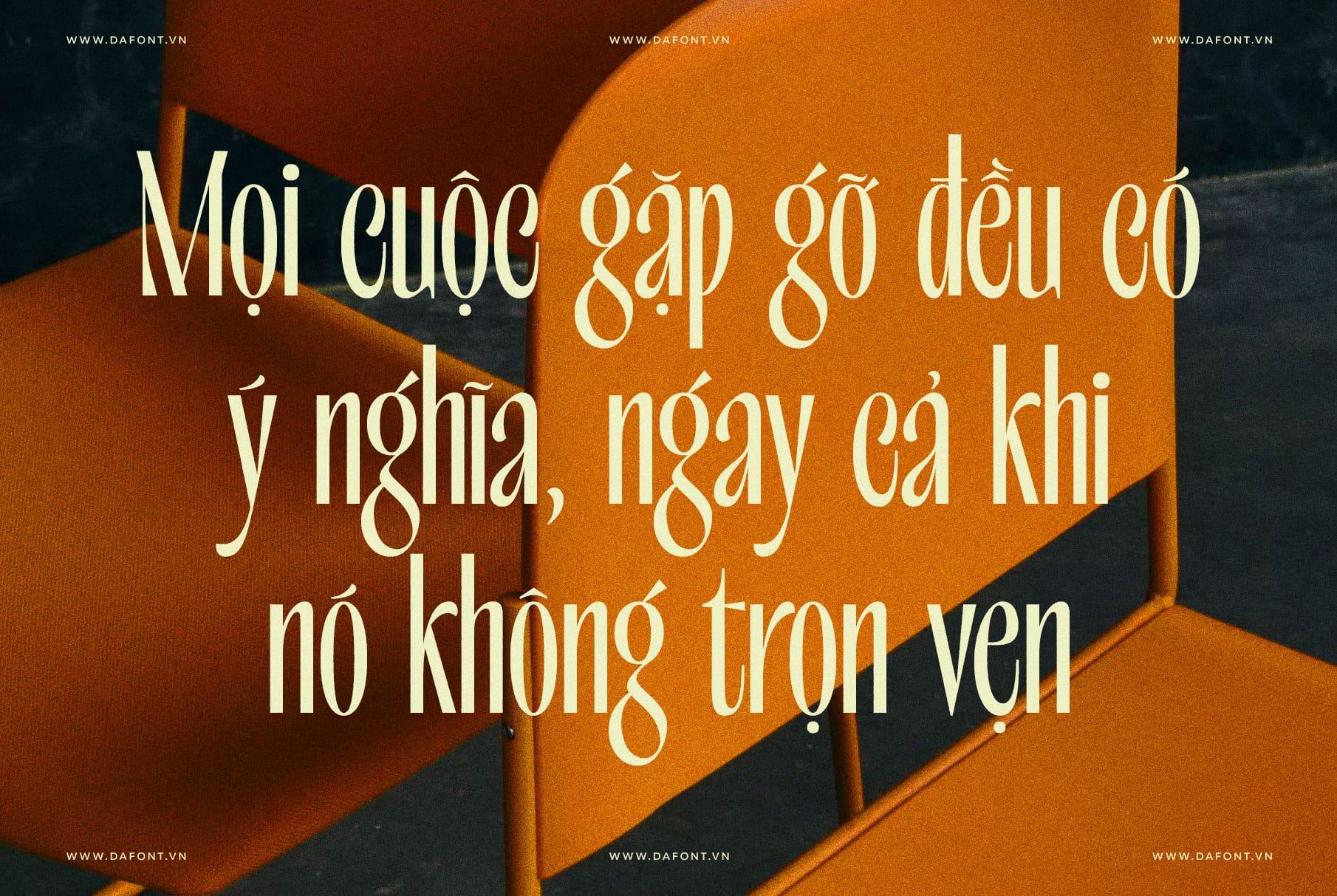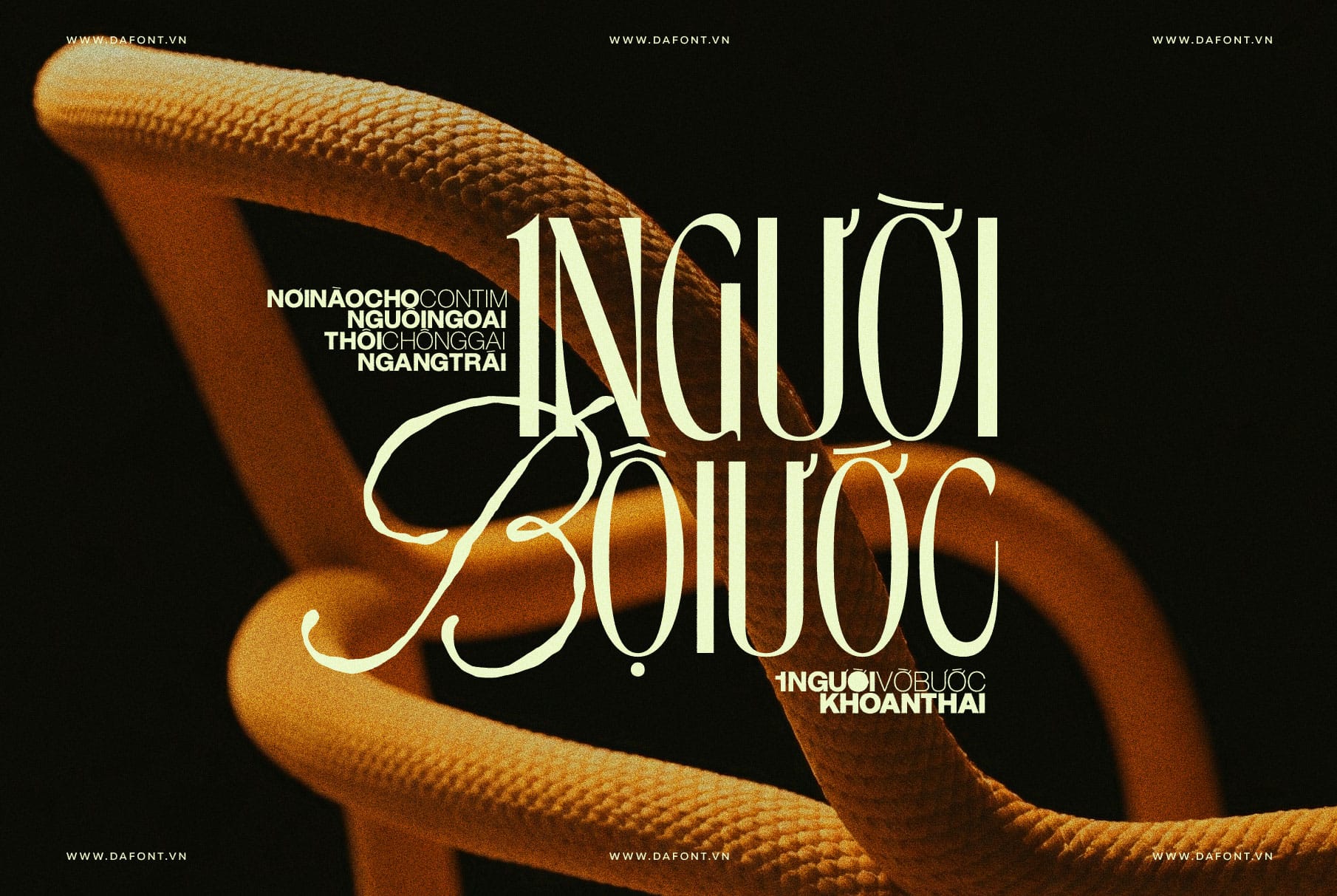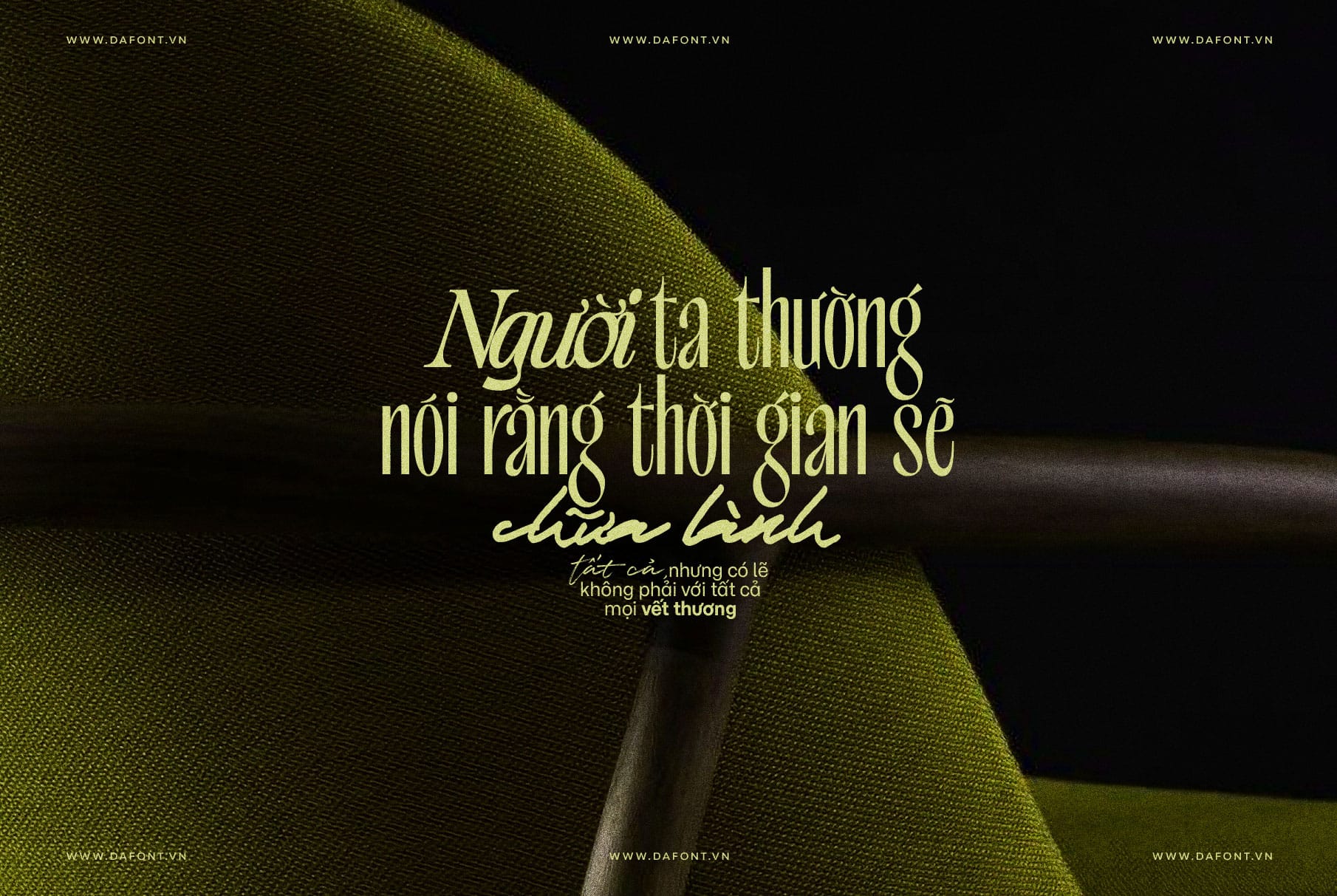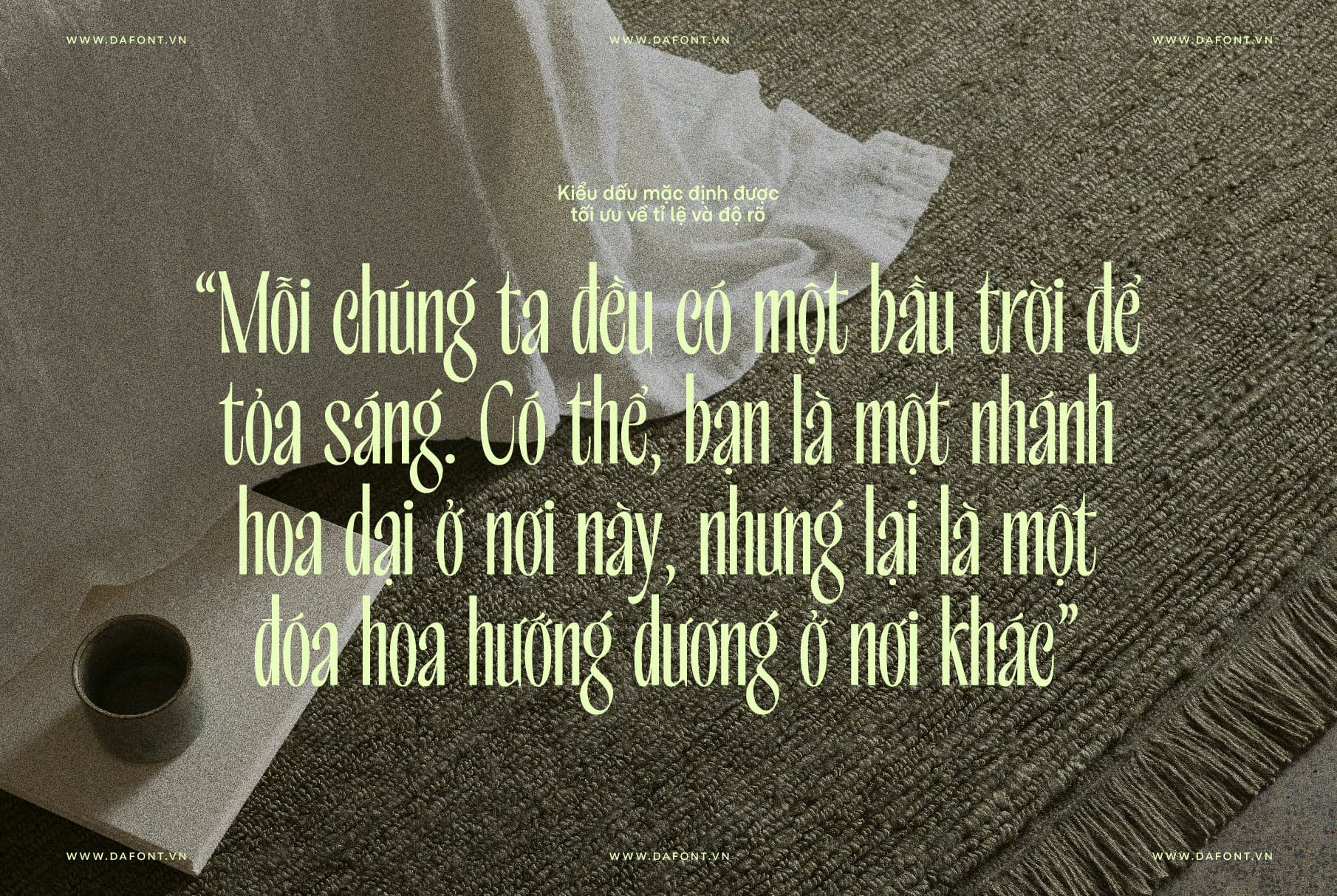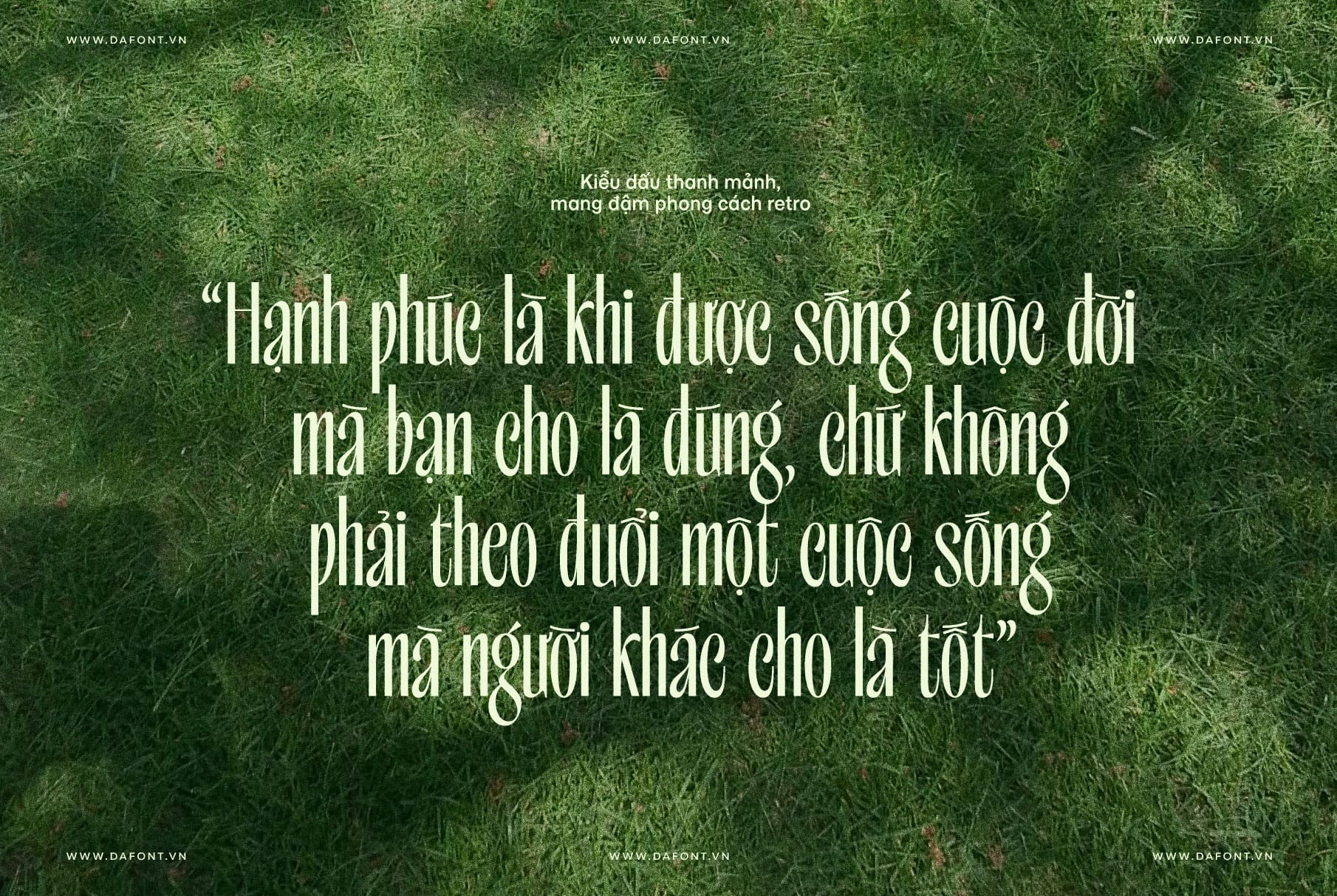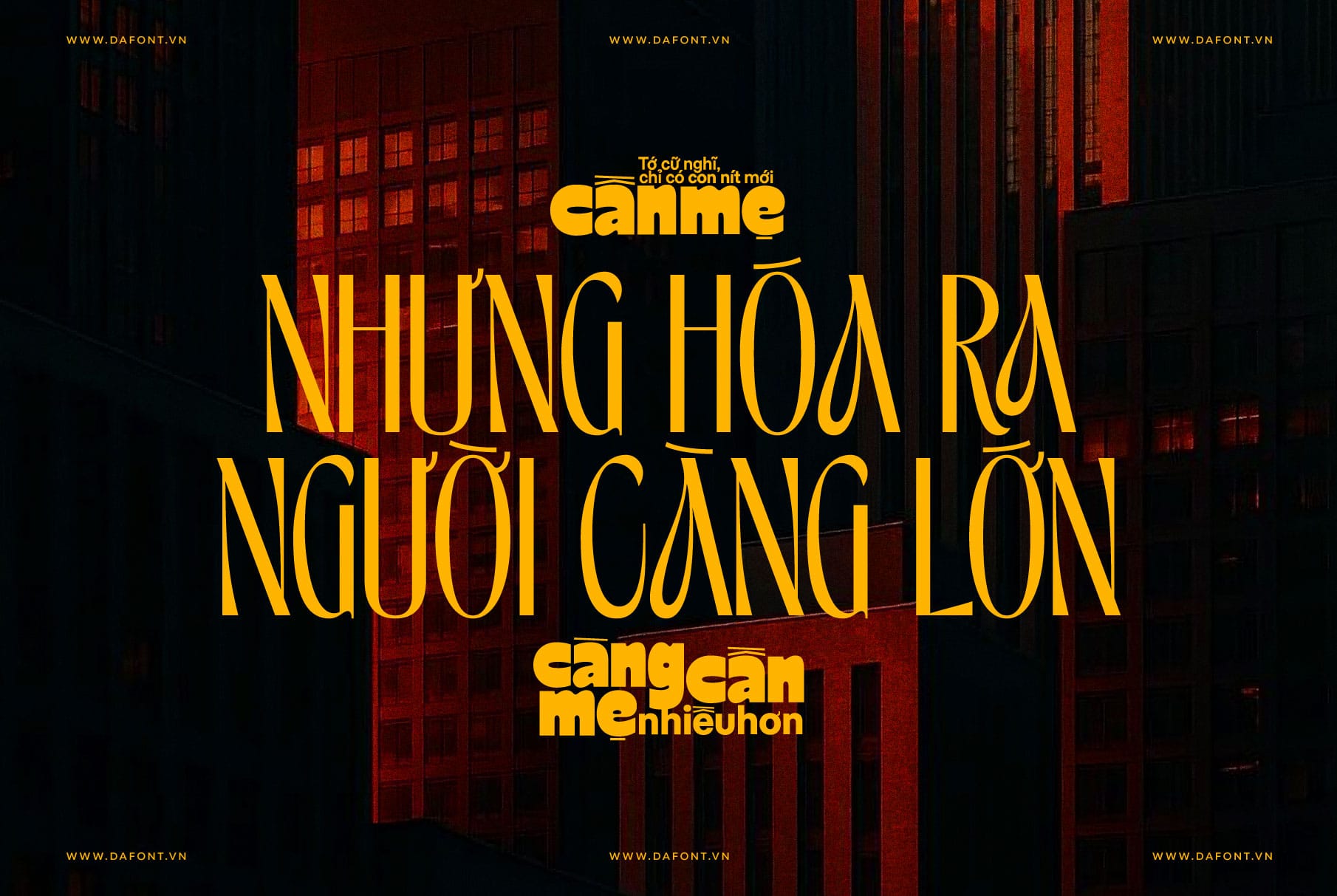
Không rườm rà, không nét thanh nét đậm quá gắt, DFVN TAN – MENAGERIE là một font modern sans-serif (Không chân hiện đại).
Font nổi bật với cấu trúc hình học lấy cảm hứng từ Art Deco, kết hợp giữa cá tính mạnh mẽ và sự tối giản thanh lịch, lược bỏ đi mọi chi tiết thừa. Kết quả là chúng ta có một font vừa mang hơi thở cổ điển của thập niên 20, vừa sở hữu sự gọn gàng, “sạch sẽ” của thiết kế đương đại.
Đặc điểm nổi bật DFVN TAN – MENAGERIE
TAN – MENAGERIE là font sans-serif hiện đại mang hơi thở Art Deco, nổi bật với cấu trúc hình học táo bạo nhưng vô cùng tối giản và gọn gàng
- Sans serif hiện đại với tinh thần tối giản (minimalist) và hình học rõ ràng
- Mang cảm hứng Art Deco đương đại, gọn gàng nhưng vẫn có cá tính
- Dáng chữ cân đối, sắc nét, tạo cảm giác cao cấp và thời trang
- Phù hợp làm headline, logo, branding hơn là body text dài
- Dễ kết hợp với layout clean, editorial và thiết kế thương hiệu hiện đại
Điểm nhấn Việt hóa
Đặc biệt, font chữ được thiết kế 2 kiểu dấu tiếng Việt linh hoạt, cho phép người dùng lựa chọn giữa phong cách gọn gàng – hiện đại hoặc mềm mại – truyền thống tùy theo tinh thần thiết kế.
- Kiểu dấu mặc định được tối ưu về tỉ lệ và độ rõ, đảm bảo khả năng đọc tốt và tính ứng dụng cao trong mọi ngữ cảnh thiết kế.
- Kiểu dấu thanh mảnh, mang đậm phong cách retro, tạo điểm nhấn tinh tế và cá tính, đặc biệt phù hợp cho các thiết kế mang hơi hướng thời trang, editorial hoặc nghệ thuật.
Nhờ đó, TAN – MENAGERIE không chỉ đáp ứng nhu cầu sử dụng chuyên nghiệp mà còn mang đến sự chủ động và sáng tạo cao hơn trong quá trình thiết kế.
Kết luận
Nếu bạn đang tìm một font để tạo branding, logo, heading, hoặc poster mà không muốn sử dụng những font quá phổ biến, DFVN TAN – MENAGERIE chính là lựa chọn hoàn hảo của bạn. Font này sẽ giúp dự án của bạn nổi bật, chuyên nghiệp, và ghi dấu lâu dài trong tâm trí người xem.